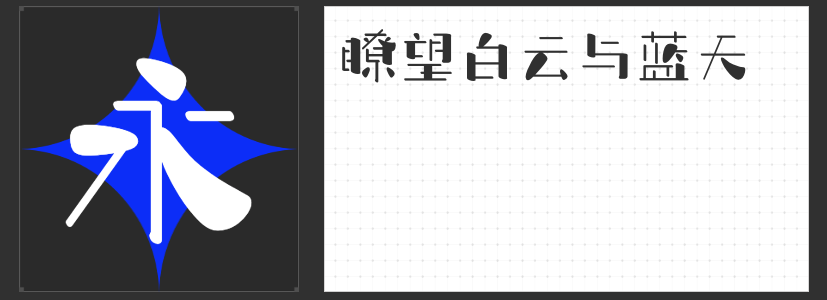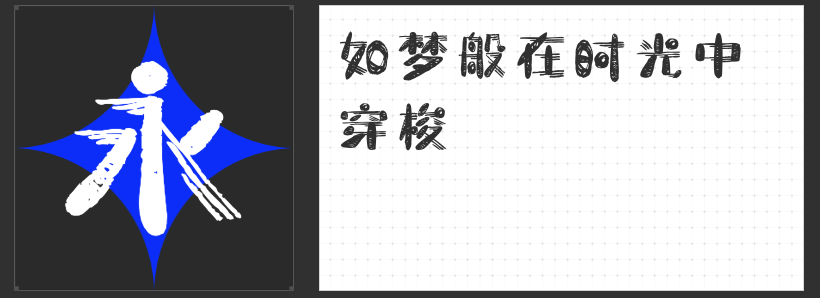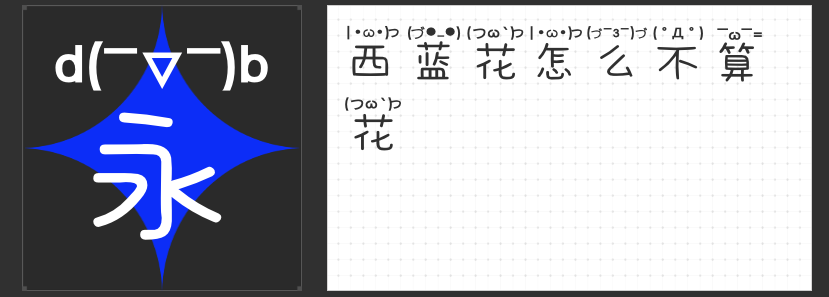
打破次元壁:四款风格化字体解锁二次元设计新维度
在二次元设计的世界里,字体不仅是信息载体,更是视觉语言的核心符号。当常规字体难以承载天马行空的创意时,以下四款风格化字体以独特的形态与性格,为角色设定、漫画分镜、游戏UI等场景注入灵魂,成为打破次元壁的视觉利器。
一、字恋狂特别黑简
这款字体以“不规整”为设计内核,通过横竖笔画的粗细极端对比构建视觉张力。横画如刀锋般锐利,竖画似铁柱般厚重,转折处保留手写时的自然抖动,形成动态失衡的节奏感。其个性张扬的形态,尤其适合需要强化角色性格的标题设计,或作为视觉符号传递反叛、热血等情绪,在赛博朋克、异能战斗等题材中能瞬间点燃氛围。
二、字圈也字可爱颜文字体
字形结构上,左低右高的倾斜角度赋予字体向前冲刺的动势,钝角与直角的交替使用则平衡了稚拙感与力量感。棱角的圆润处理暗含亲和力,而尖锐转角又透露出不服输的倔强。这种“外柔内刚”的矛盾美学,恰似二次元角色中常见的“傲娇”性格,既可塑造元气少女的对话框,也能诠释热血少年的内心独白,让文字本身成为角色人格的延伸。
三、字恋狂白日梦简
凌乱的线条如被风吹散的发丝,笔画间若隐若现的留白仿佛时光的裂隙。这款字体摒弃了传统字形的规整性,以“不完美”模拟梦境的朦胧质感。其飘逸的笔触适合描绘幻想场景的旁白,或作为心理活动的视觉化表达,在绘本、漫画分镜中营造出“意识流”般的叙事氛围,让读者瞬间沉浸于角色的幻想世界。
四、字恋狂石头简
细笔画以几何线条勾勒骨架,末端却突然晕染出毛笔笔触的肌理;粗笔画如石块堆砌,却在交接处刻意断开,形成破碎的视觉错觉。这种“矛盾修辞”般的设计语言,既保留了手写字体的温度,又融入了超现实主义的荒诞感。在解谜游戏、奇幻漫画等需要营造神秘氛围的场景中,其错位结构能激发观众的好奇心,引导视觉探索的轨迹。
二次元设计的本质是“造梦”,而这四款字体恰似通往异世界的钥匙——它们以形态传递情绪,用结构讲述故事,让文字超越语言本身,成为连接现实与幻想的视觉纽带。当设计需要突破常规时,不妨让这些字体成为你的创意伙伴,共同开启一场次元穿越的视觉冒险。